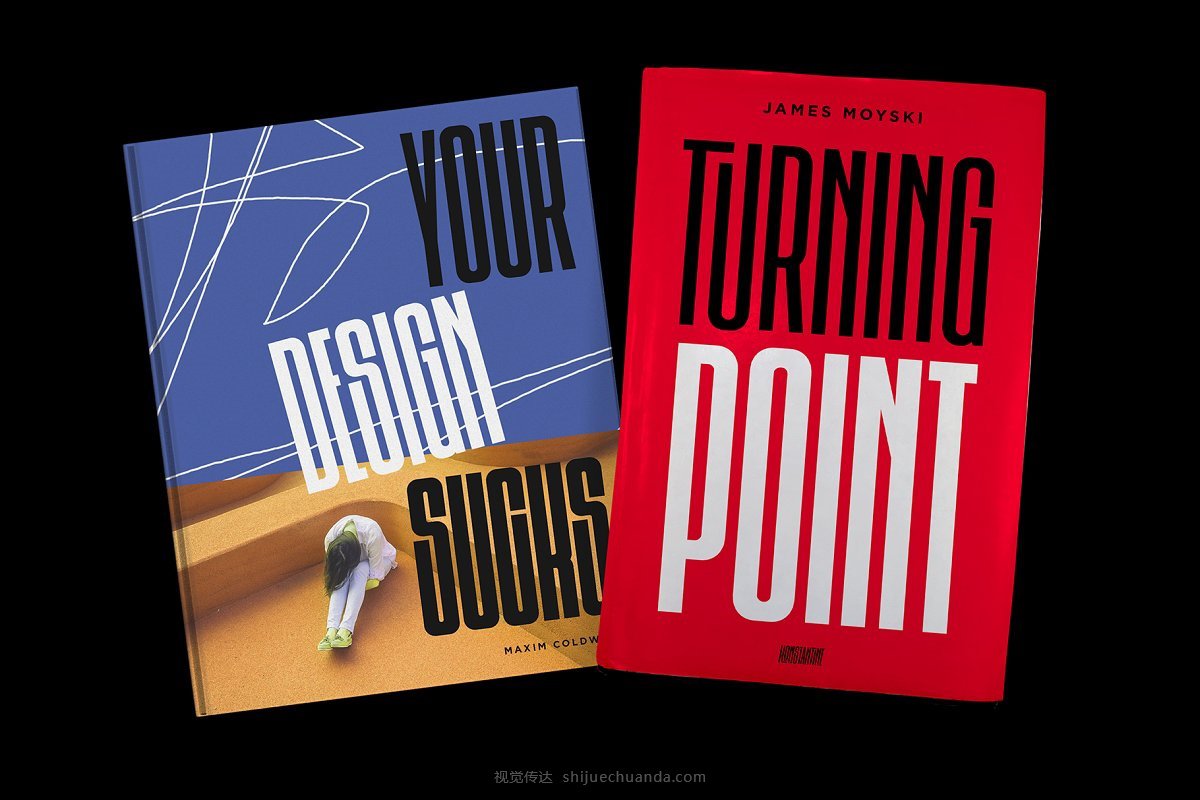
力量运动科技感英文杂志海报排版字体 Urbanshock-Condensed Display Sans
一种前卫的浓缩显示无衬线字体,具有非常不寻常的氛围。根本不是典型的无衬线字体。
非常适合书籍封面、海报、专辑插图、音乐项目、艺术活动、艺术画廊、嘻哈品牌、视觉活动、徽标、品牌、网站、社交媒体内容。